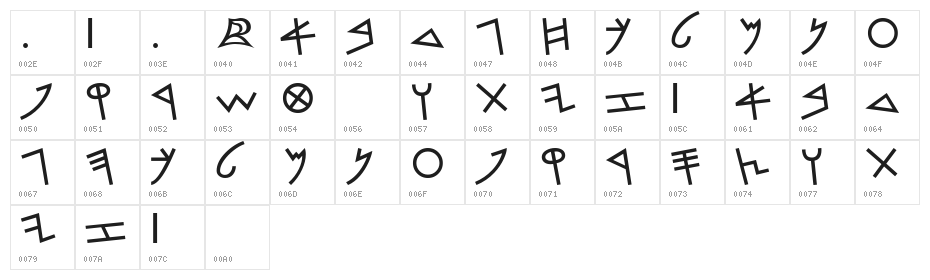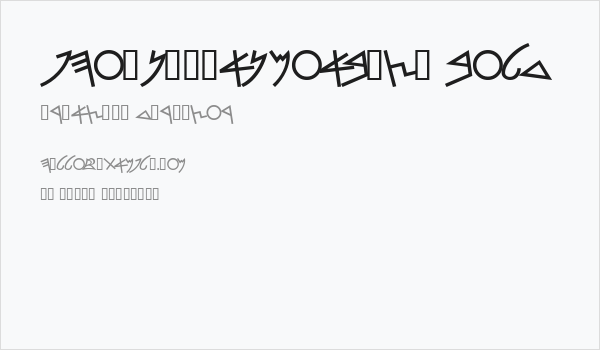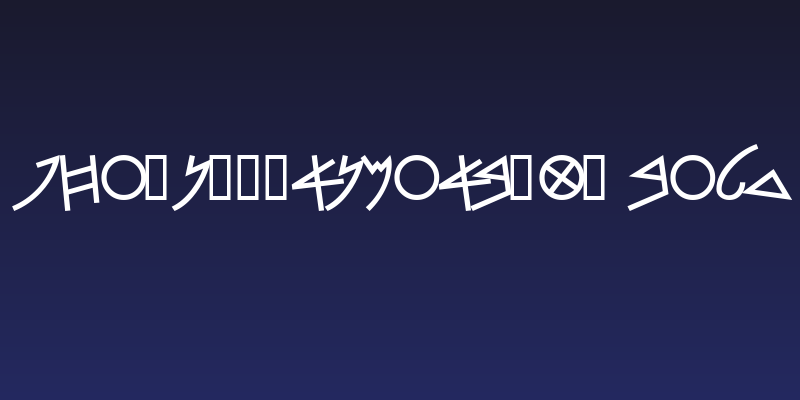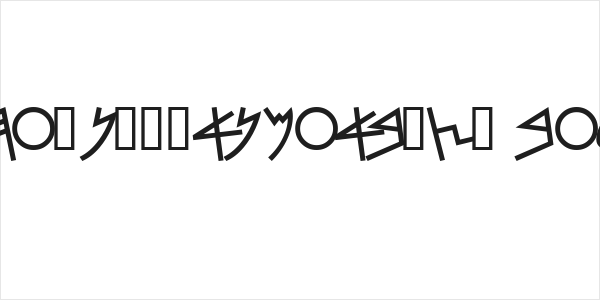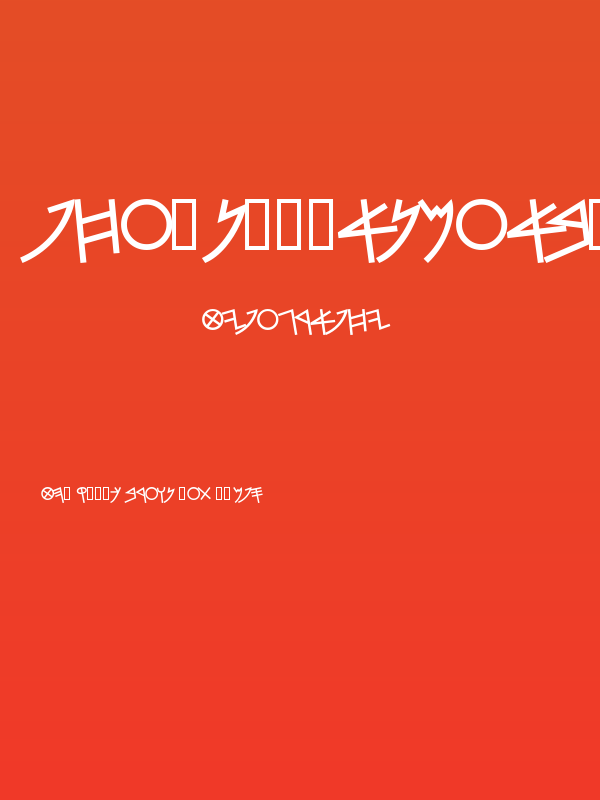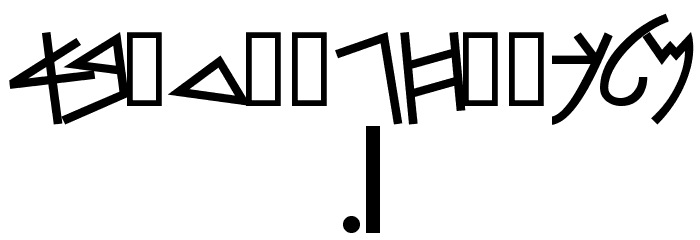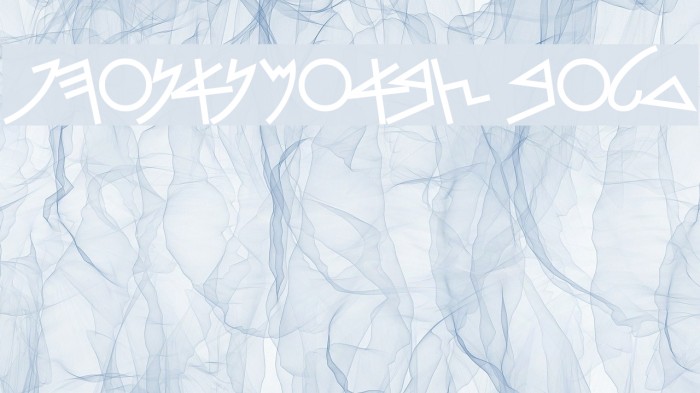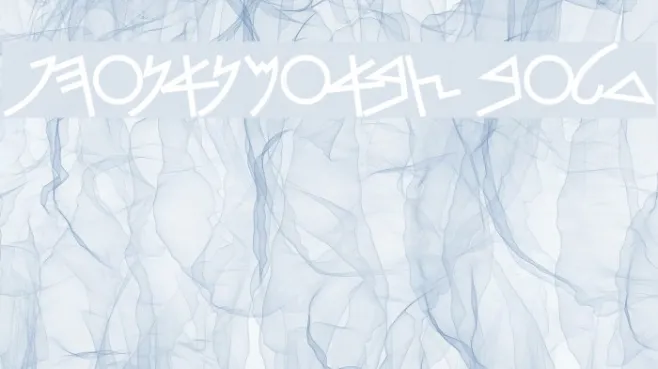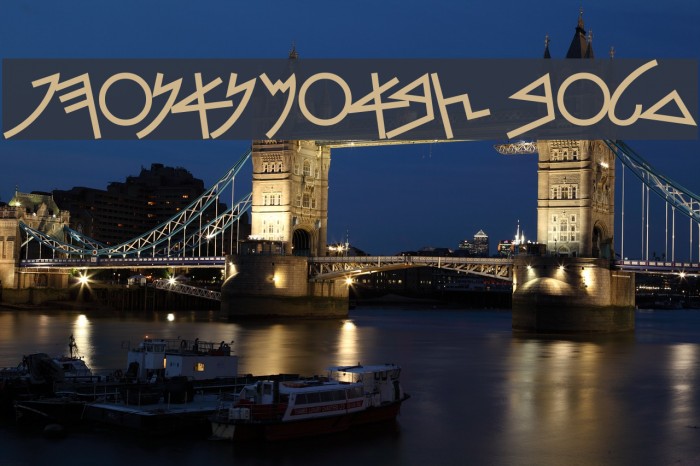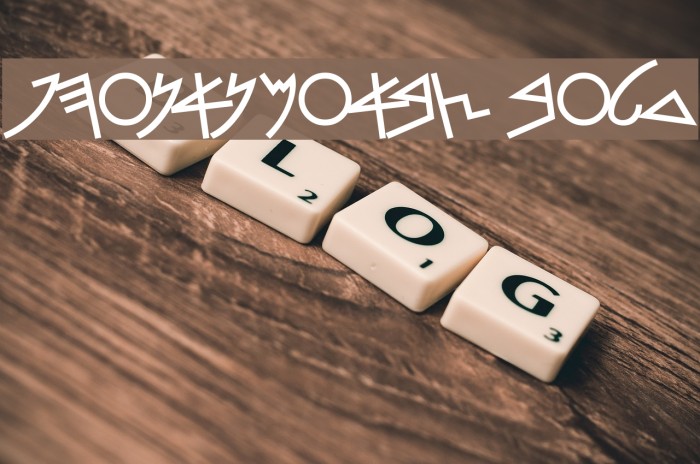
PhoenicianMoabite Bold Font
| Cas d'utilisation | Logos, Posters, Themed Events |
| Projets proposés | Ideal for historical or cultural projects, themed posters, book covers, and logos that require an ancient or mystical aesthetic. |